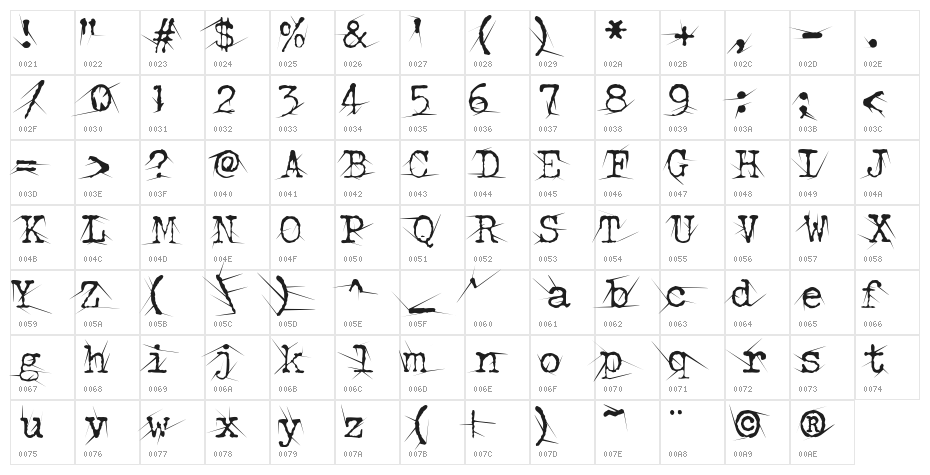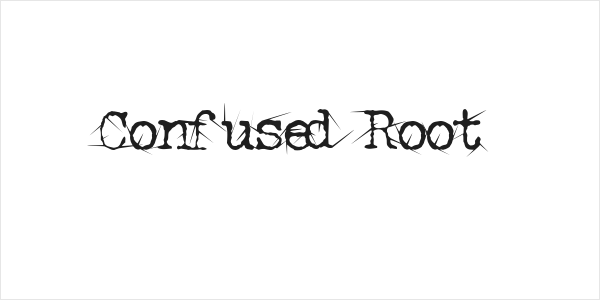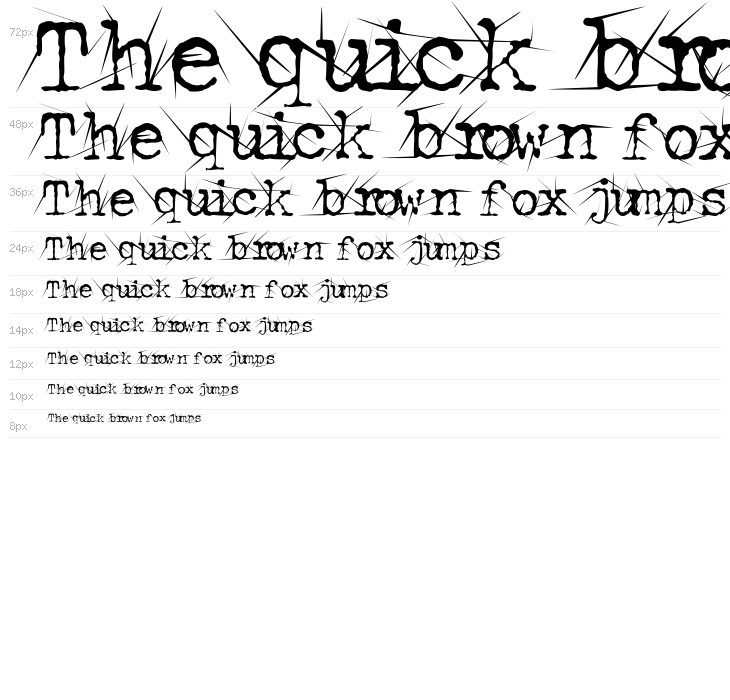
Confused Root Font
Fonts by Abstract Type Design - Patrick Durr
| Progetti proposti | Ideal for horror-themed designs, edgy posters, album covers, and any project needing a bold, unconventional look. |